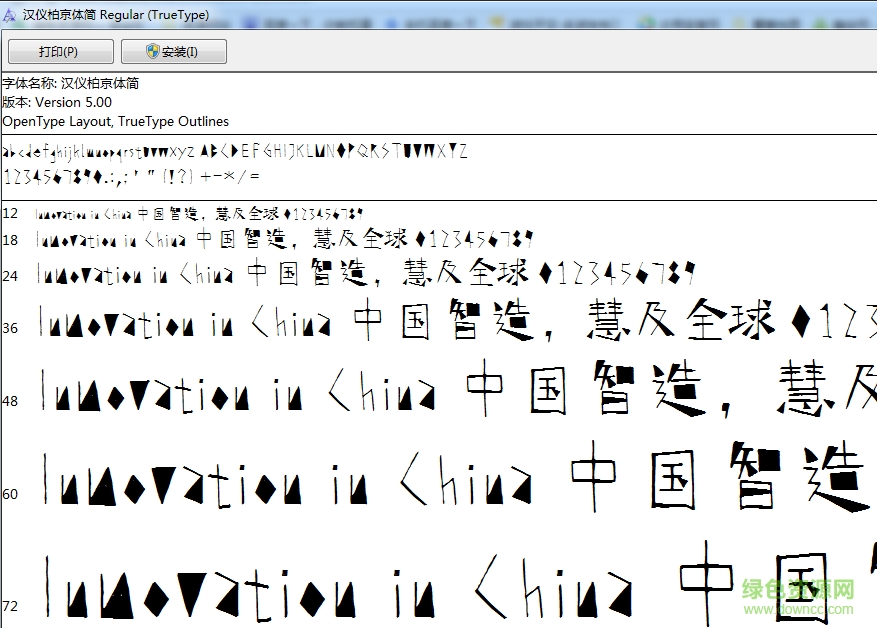
漢儀柏京體是漢儀字體中的一款很有現(xiàn)代藝術(shù)體特色的字體,且字體完整不缺字,給你不同的輸入打字體驗(yàn),可用于廣告、名片、包裝等設(shè)計(jì),歡迎大家在綠色資源網(wǎng)下載使用!
漢儀柏京體技術(shù)上借鑒了歐式傳統(tǒng)鋼筆的剛勁筆鋒, 三角形和線條的組合產(chǎn)生了表現(xiàn)主義的豪放效果。字體風(fēng)格活力蓬勃,筆勢伸展如龍蛇舞動,同時(shí)又受歐陽體的影響,結(jié)構(gòu)布局是平正工整,嚴(yán)謹(jǐn)峭勁,有疏有密,穩(wěn)中而生動??梢詰?yīng)用于廣告設(shè)計(jì)、名片設(shè)計(jì)、包裝印刷、產(chǎn)品設(shè)計(jì)等應(yīng)用。